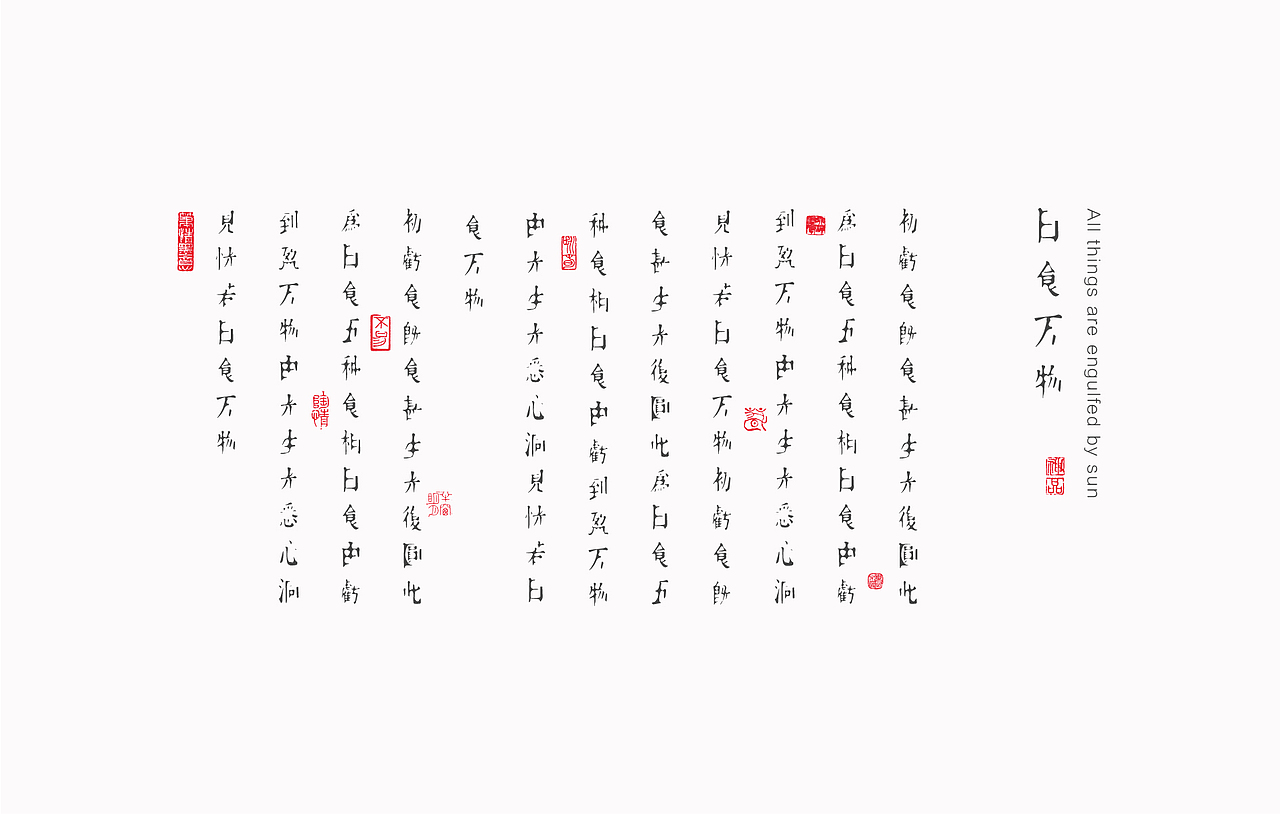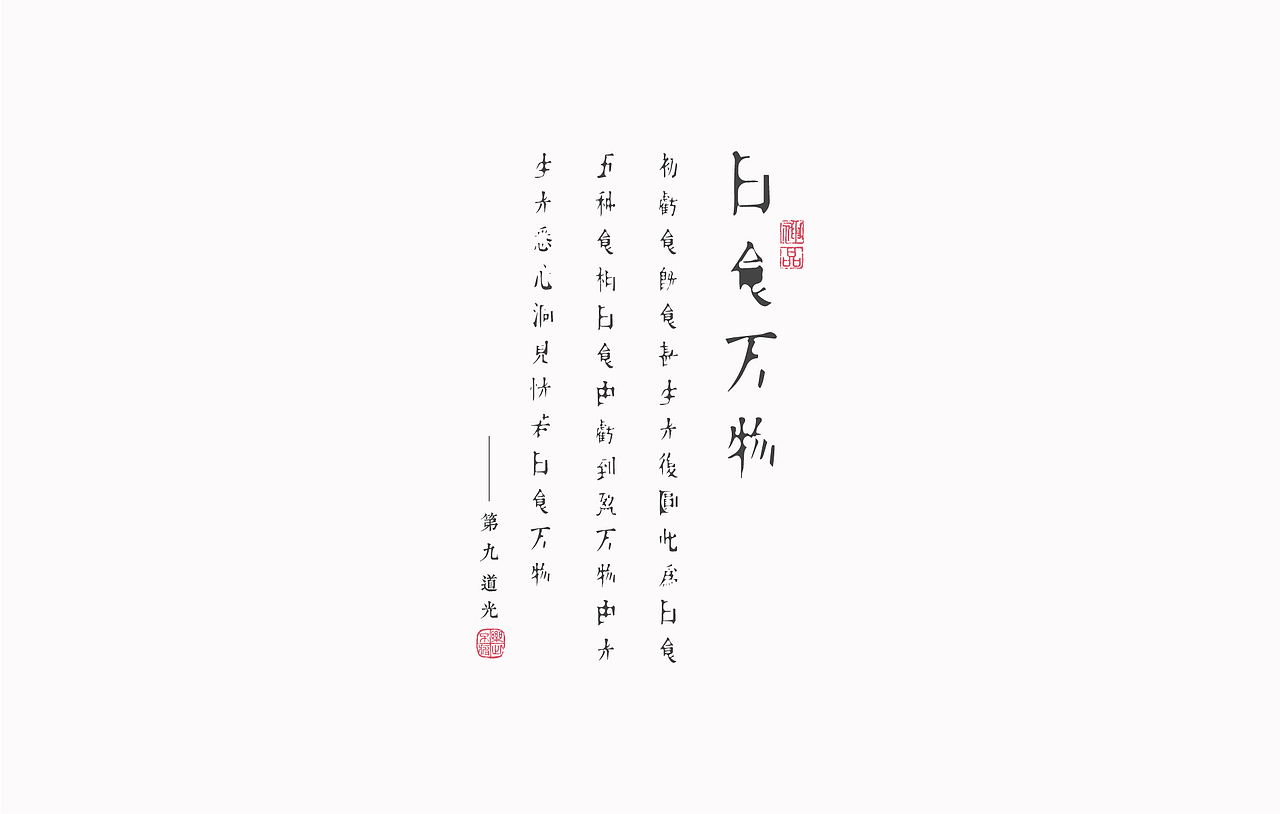
日食万物——残缺字体实验
我以残缺为美.我发现中文字体在缺失某一部分的时候,依然保持着完整的识别性.我将这个发现放大,用圆进行字体分割实验,仿照日食的感觉.字体残缺的同时又保持美观,故名《日食万物——残缺字体实验》
古文排版效果
实体及描边效果
竖排版及提名
标志应用示例
标志应用示例效果图
标志应用示例效果图2